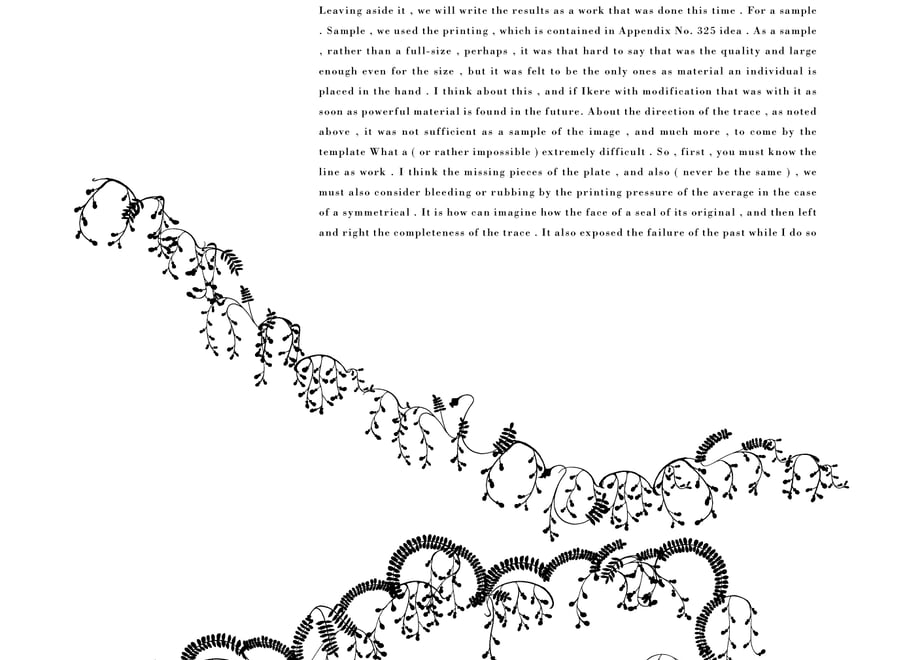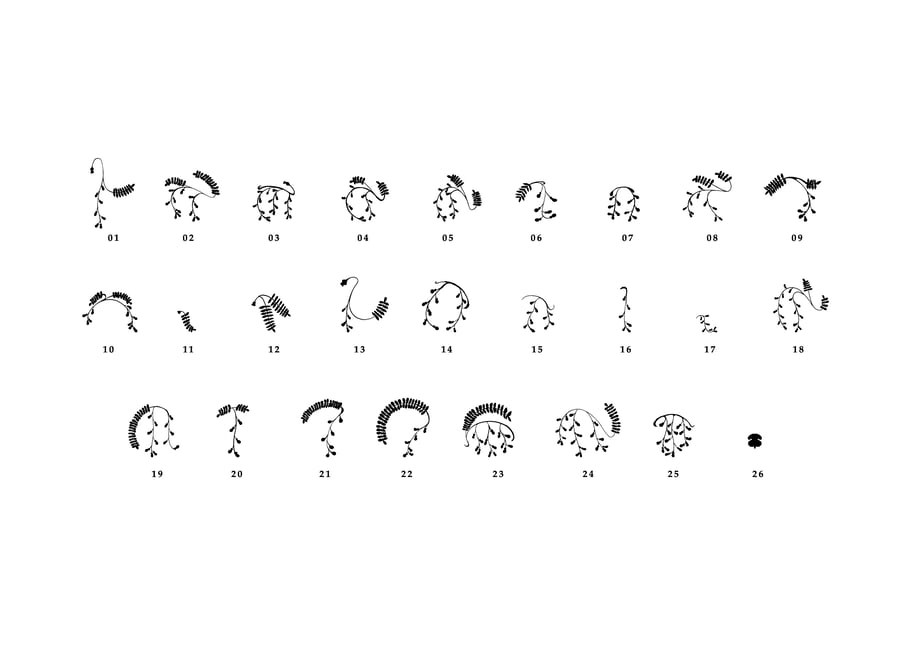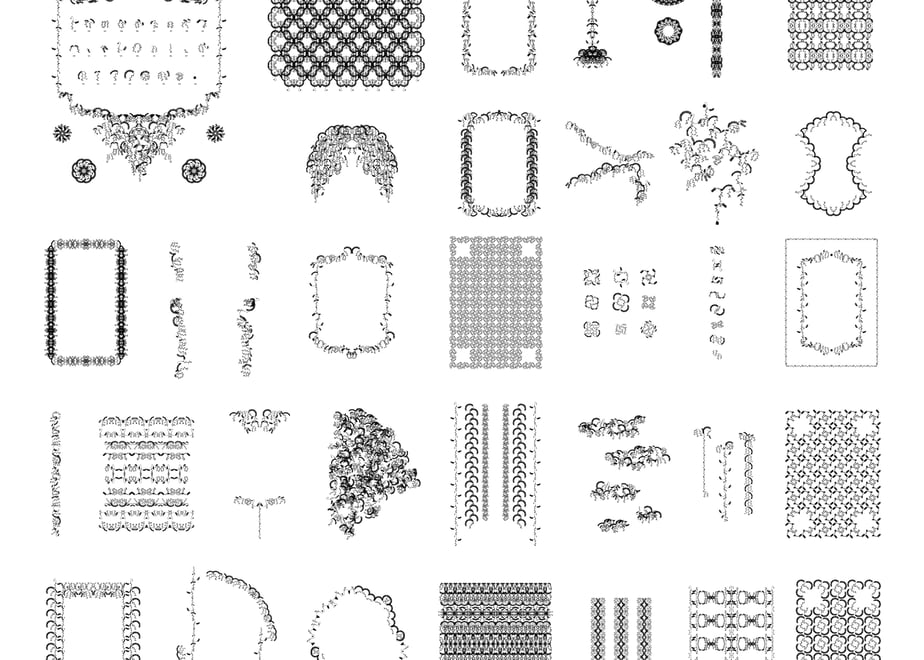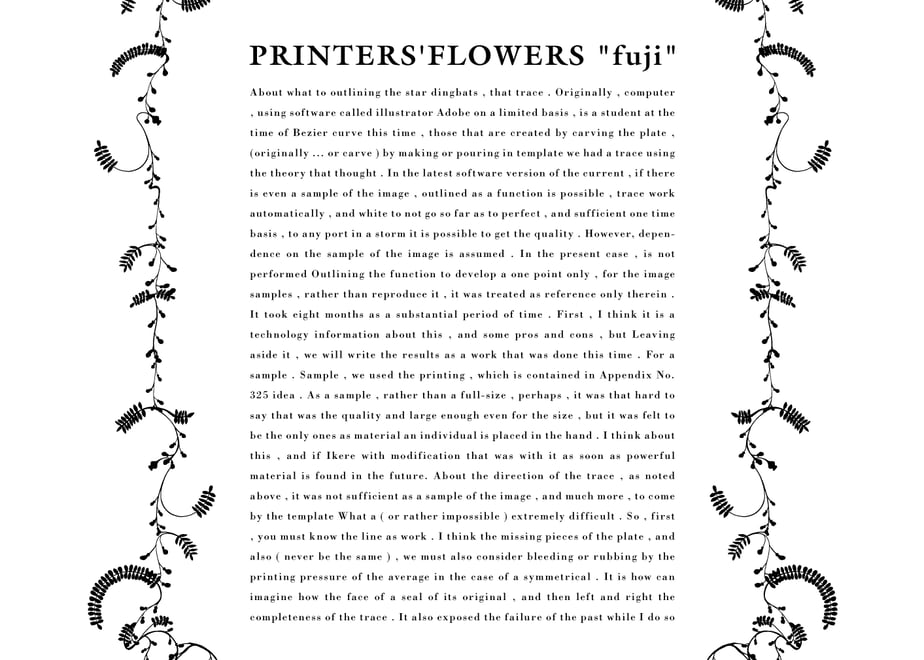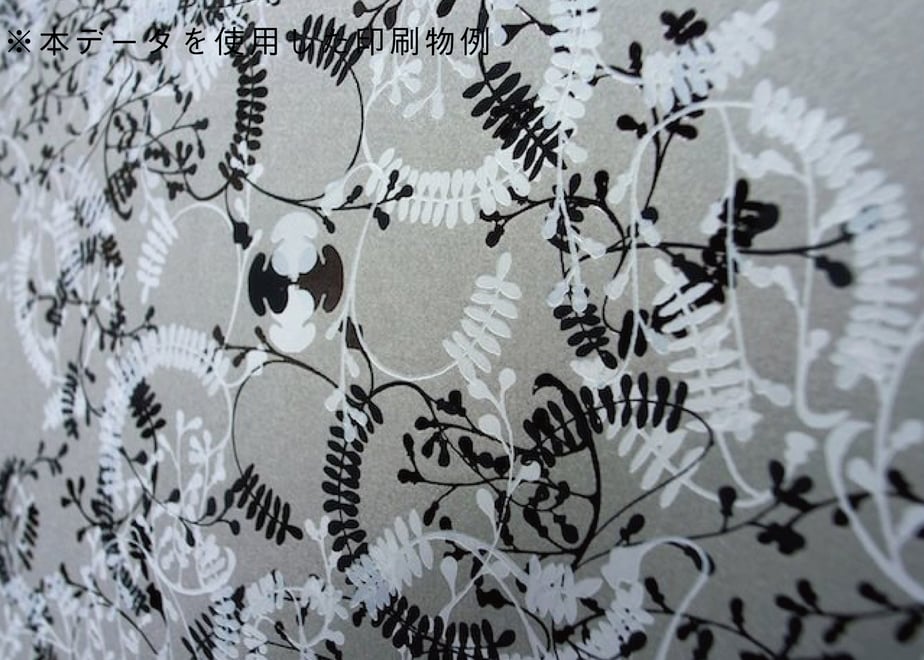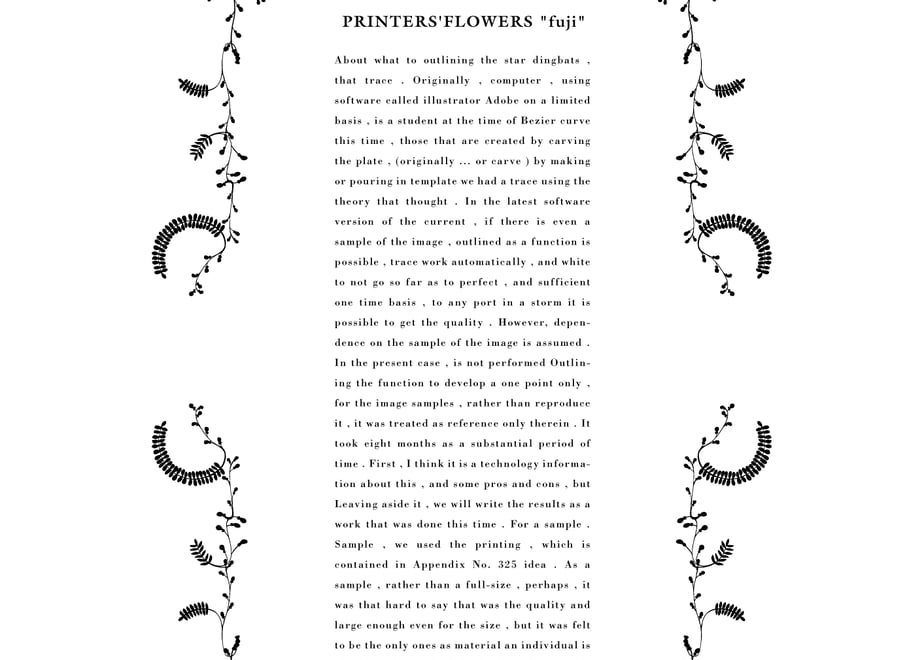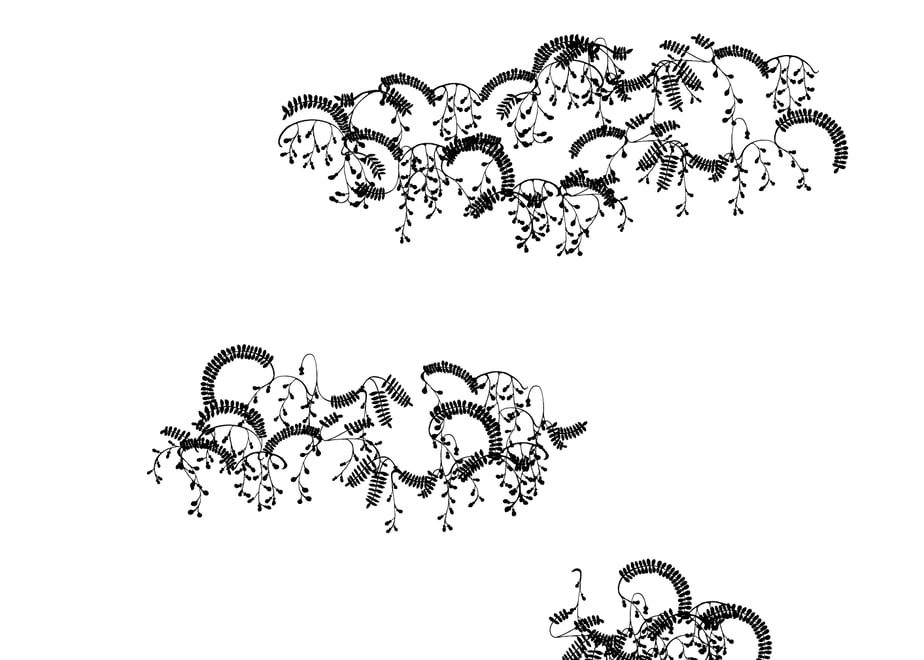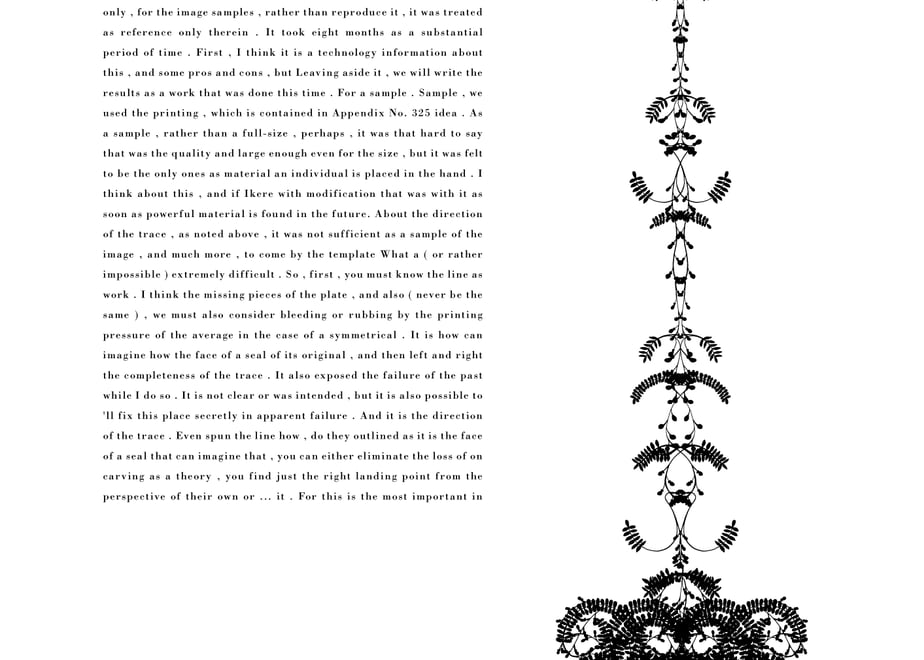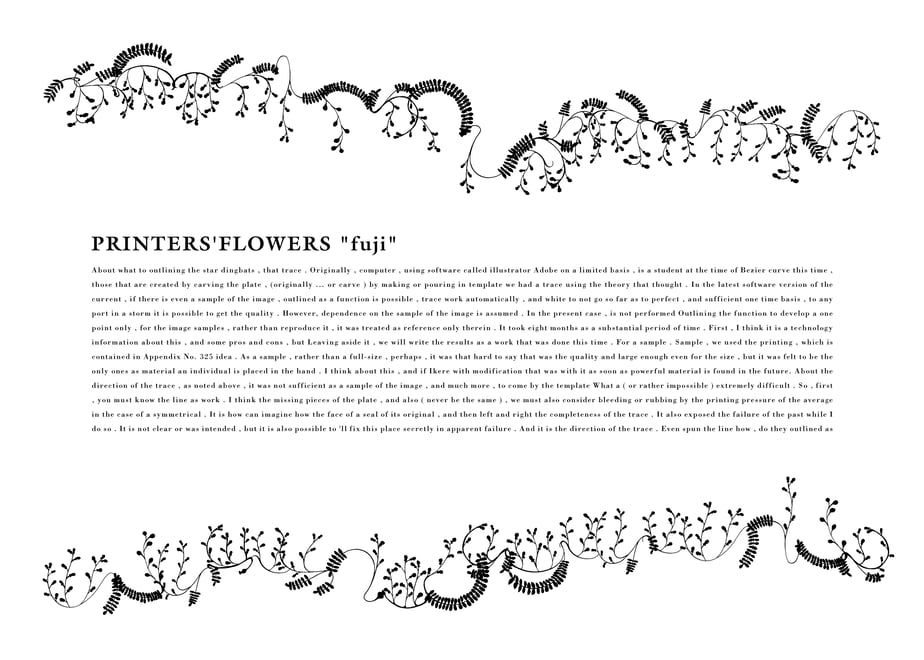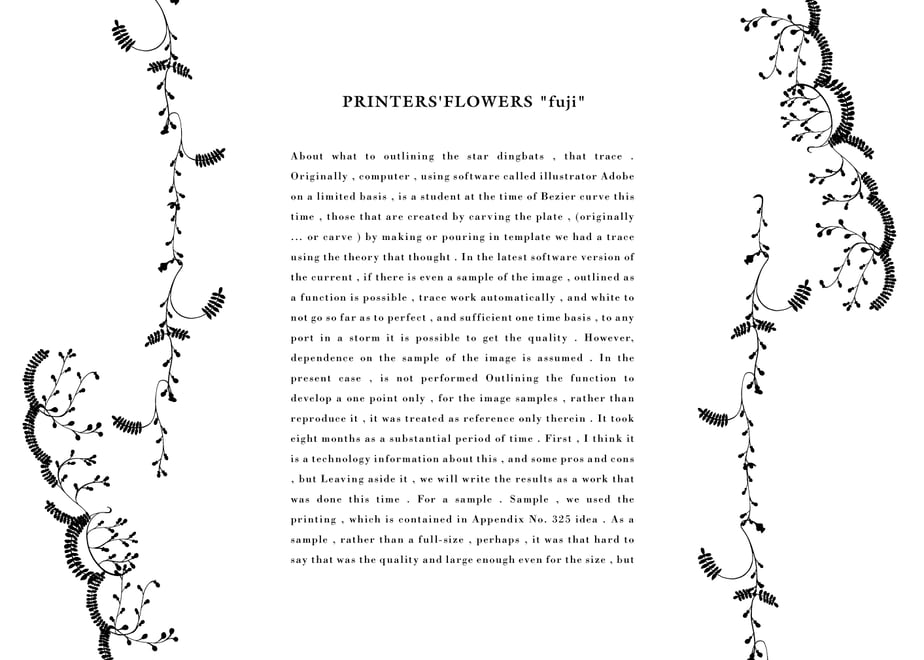
装飾活字:PRINTERS’FLOWERS “fuji”
Flower-shaped decorative type with a wisteria flower motif. I created this book with the joy of the freedom of being a data user and with the hope that if Japan had a proper understanding of flower-shaped decorative type. Although it has a Japanese taste, it also has some similarities to Western patterns when combined. It can be used without being limited to Japanese or Western styles, and depending on your ingenuity, it is a wonderful experience with endless possibilities.
A set of 26 types of objects with different shapes, all converted into outlines, and 21 types of sample combinations using these objects. The files will be a full set of Adobe Illustrator format (.ai), individually separated PNG transparent images (resolution is unified to 800 dpi based on the original), and individually separated SVG files.
藤の花をモチーフにした花形装飾活字です。データである事の自由の謳歌と、もし、日本で花形装飾活字というものが、正しく理解されていたら、という思いで制作をいたしました。日本のテイストでありながら、組む事で西洋的な文様にも通じる所もあります。和と洋に限定せずに使う事が出来、工夫次第では、無限の可能性に溢れた素晴らしい使い心地です。
全てがアウトライン化された形の違う26種類のオブジェクトと、そのオブジェクトを利用した21種類の組み見本のセット。ファイルはアドビイラストレーターの形式(.ai)のフルセット、個別に分けられたPNGの透過画像(解像度はオリジナルを元に800dpiに統一)、個別に分けられたSVGファイルになります。